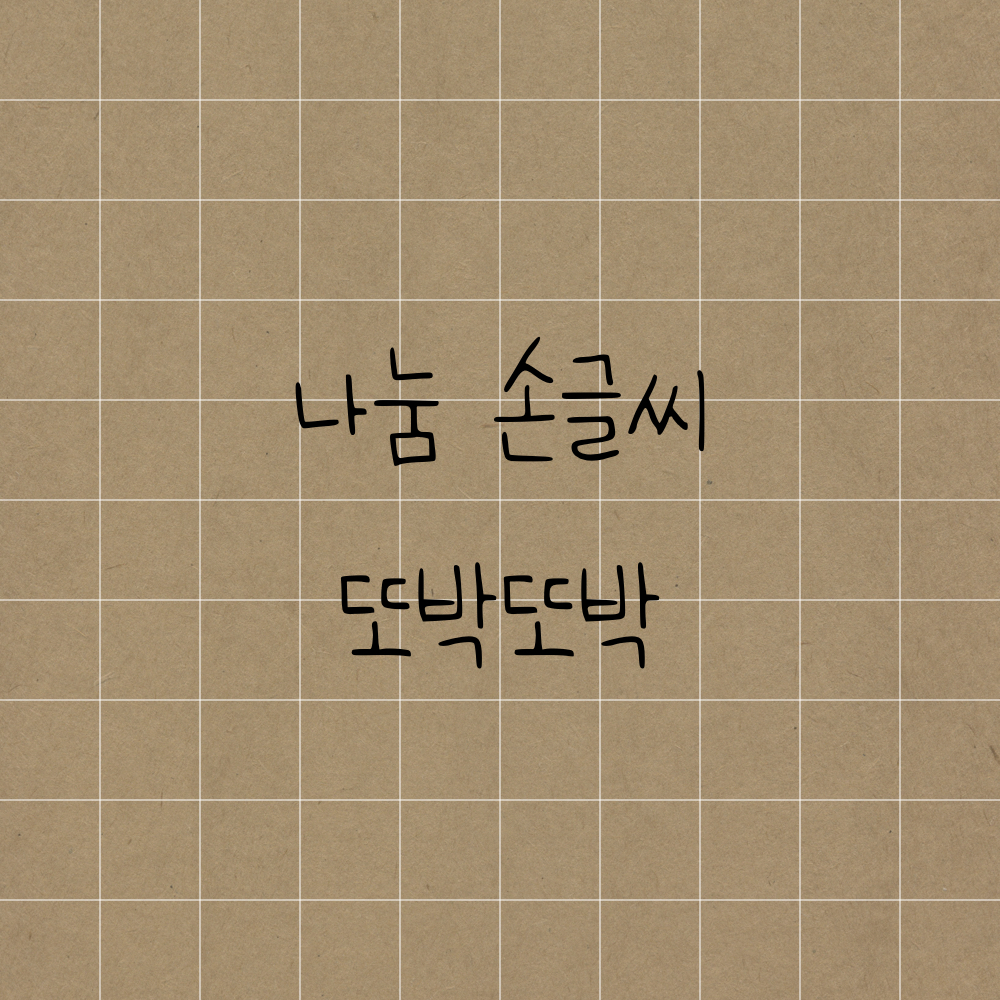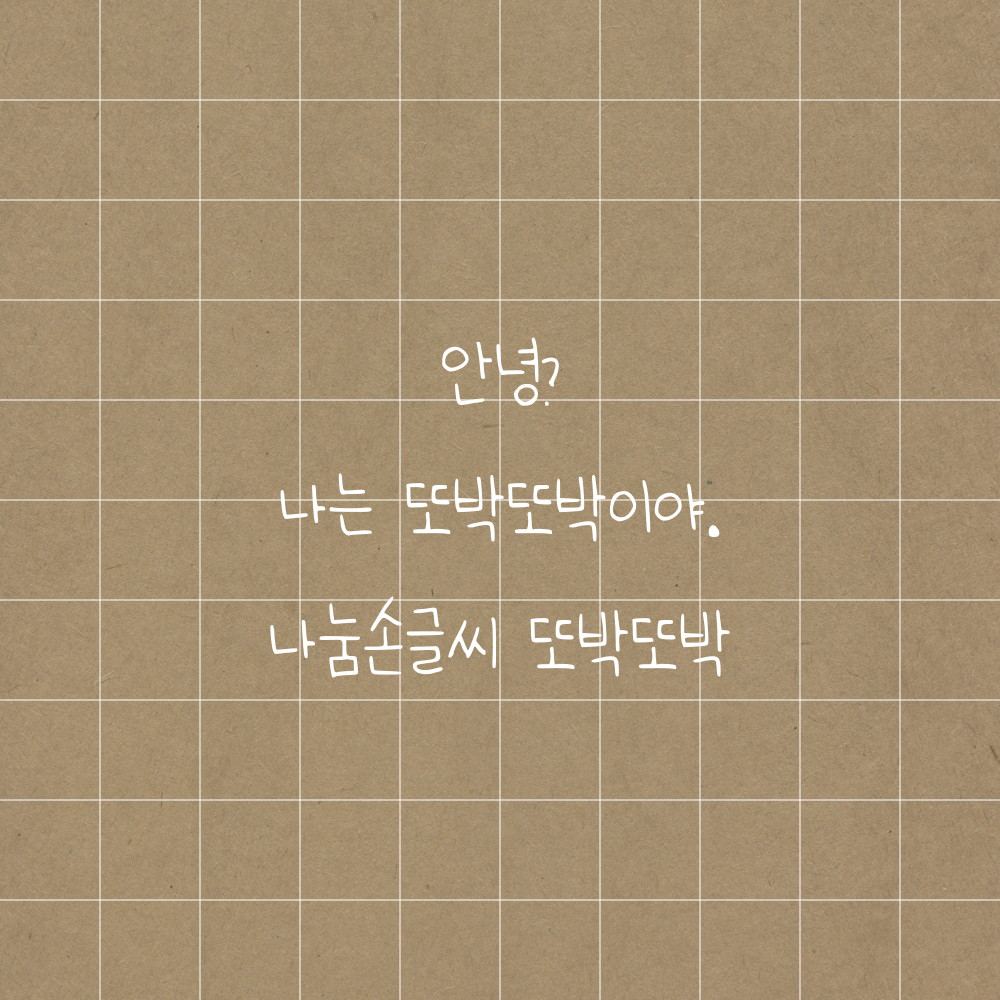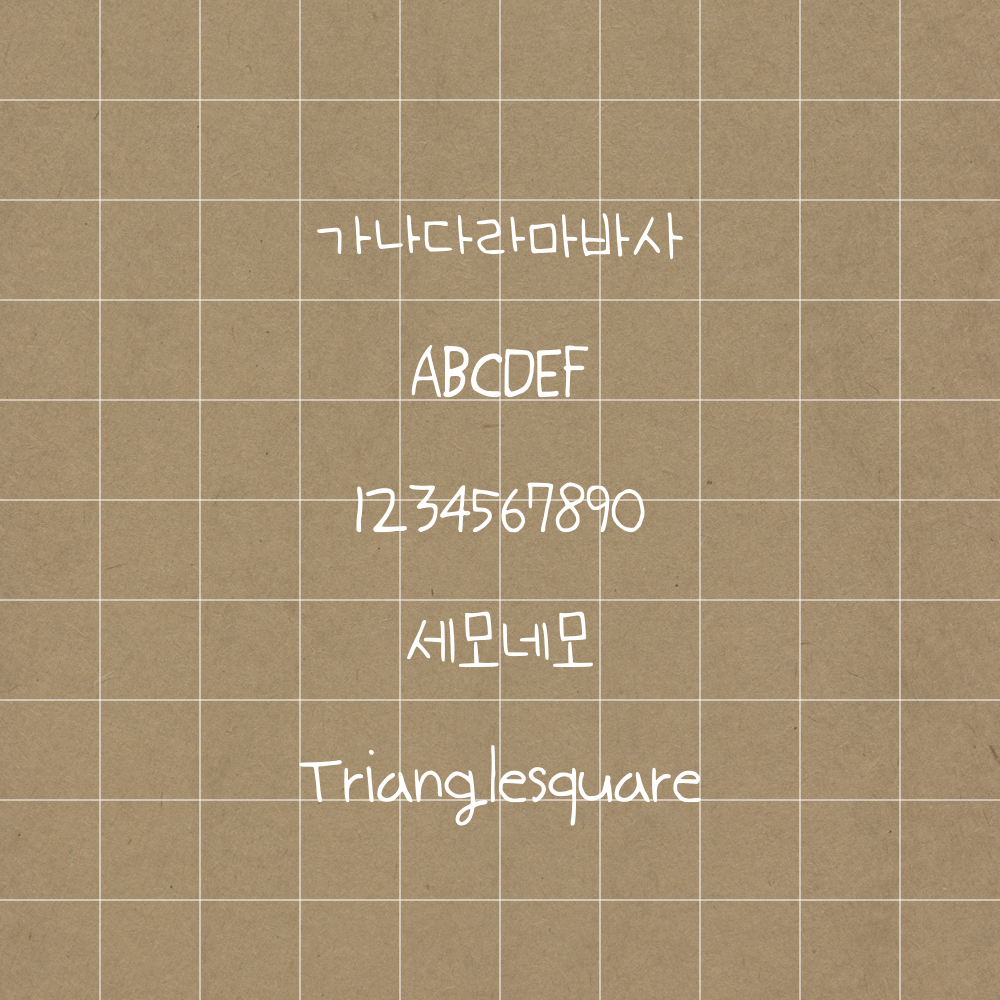
오늘의 폰트는 또박또박체입니다💛
초등학교 3학년이 만든 폰트라서 글씨체 이름이 또박또박인가 봅니다.10살의 글씨체라니,, 내 손,, 주머니로 들어가,,😂
모서리가 둥글둥글해서 어떤 글씨를 적어도 귀여운 컨셉으로 보이네요😆
폰트의 굵기가 얇아서 필기 본문에 파스텔 색상과 사용하기 좋은 폰트입니다💛